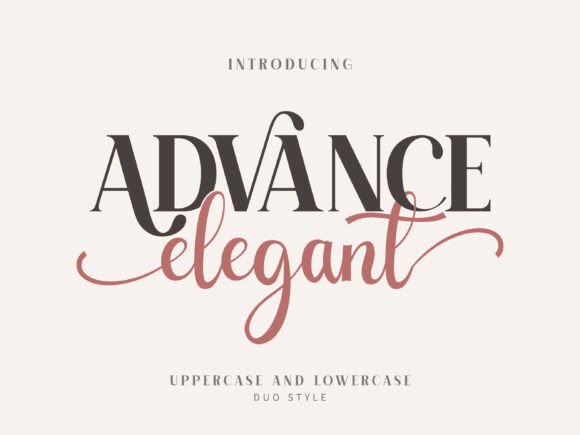
Advance Elegant
Si vous recherchez des ressources de haute qualité comme Advance Elegant, ce pack premium est un choix fantastique pour vos projets créatifs.
Conçu avec précision, Advance Elegant offre des vecteurs nets, une typographie fluide et une licence commerciale pour une tranquillité d'esprit.
Que vous créiez des produits POD (impression à la demande), des invitations de mariage ou des visuels pour les réseaux sociaux, Advance Elegant est un choix idéal.